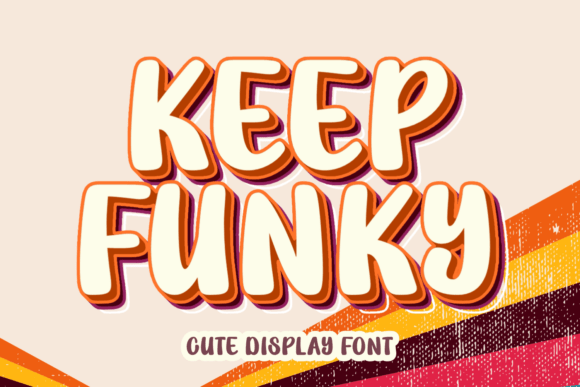
Keep Funky
قد يكون العثور على عناصر التصميم المناسبة أمرًا صعبًا، ولكن Keep Funky يقدم مجموعة استثنائية ترتقي بعملك على الفور.
سواء كنت تقوم بإنشاء منتجات الطباعة عند الطلب أو دعوات الزفاف أو رسومات وسائل التواصل الاجتماعي، فإن Keep Funky هو الخيار المثالي.